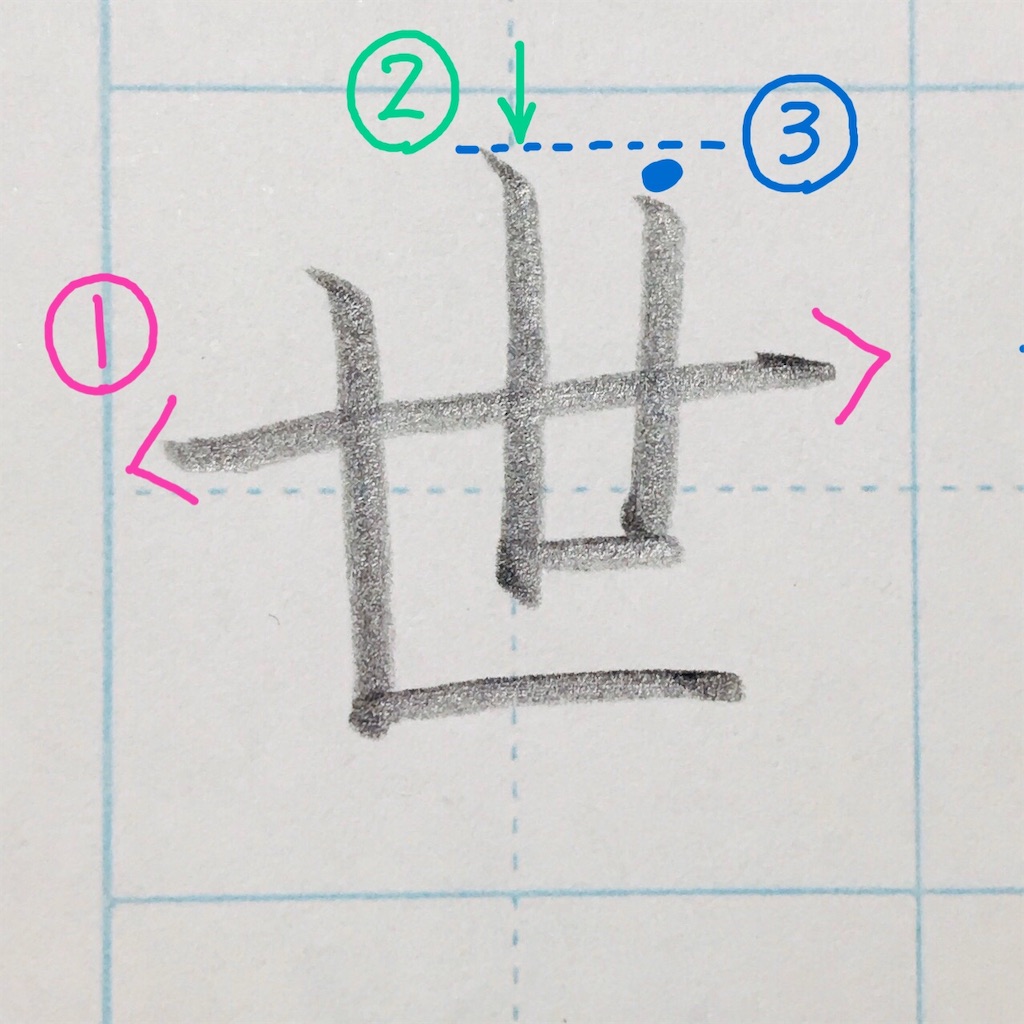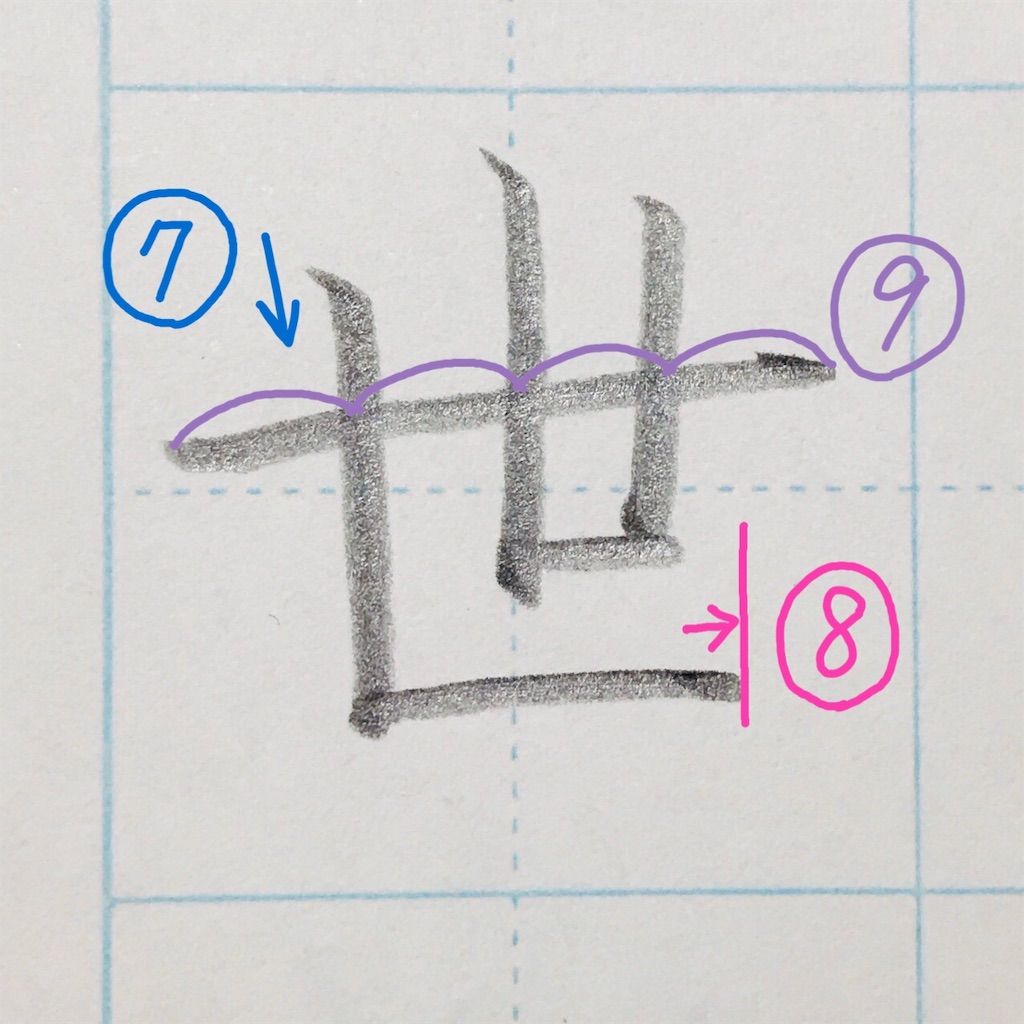
「世」のきれいな書き方。
今回は、「世」の書き方を解説します。
「世」の見本
「世」の書き順
「世」のポイント
①右上がりに。長く強調。
②中心に、まっすぐ。
③少し低くする。
④ほんの少し斜めにする。
⑤「縦」と「横」を出す。
⑥3画目よりも少し低く。
⑦3画目と同じ角度で、ほんの少し斜めに。
⑧3画目よりも少し右で止める。
⑨等間隔。
⑩1対1に。
★狭めに。広く空くと、間延びしてしまうので注意。
完成!